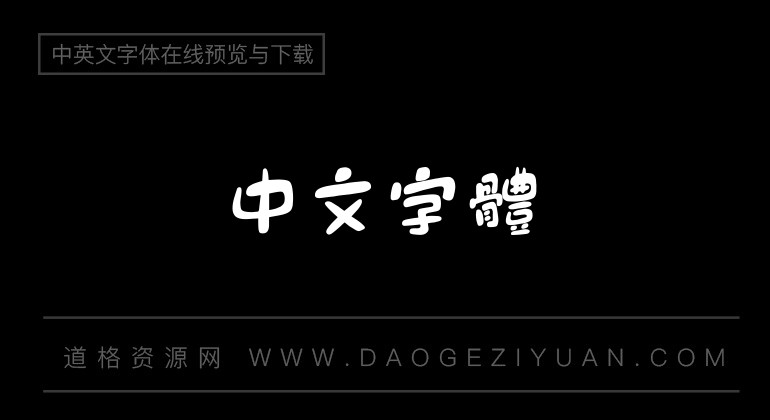
腾祥面包体繁体
腾祥面包体繁体字体是由深圳腾祥科技有限公司推出的一款繁体字体,它是一款简洁大方的繁体字体,具有良好的美感,能够很好地表现文字的精细度,可以帮助用户在设计中更好地表达自己的想法。此外,它还具有良好的可读性,可以帮助用户更好地理解文字的内容。
腾祥面包体繁体是一款非常不错的手写艺术字体,具有很好的视觉感,适合于文化类的宣传设计、商业类品牌的广告和产品包装设计以及个性化文字排版等较多场景。